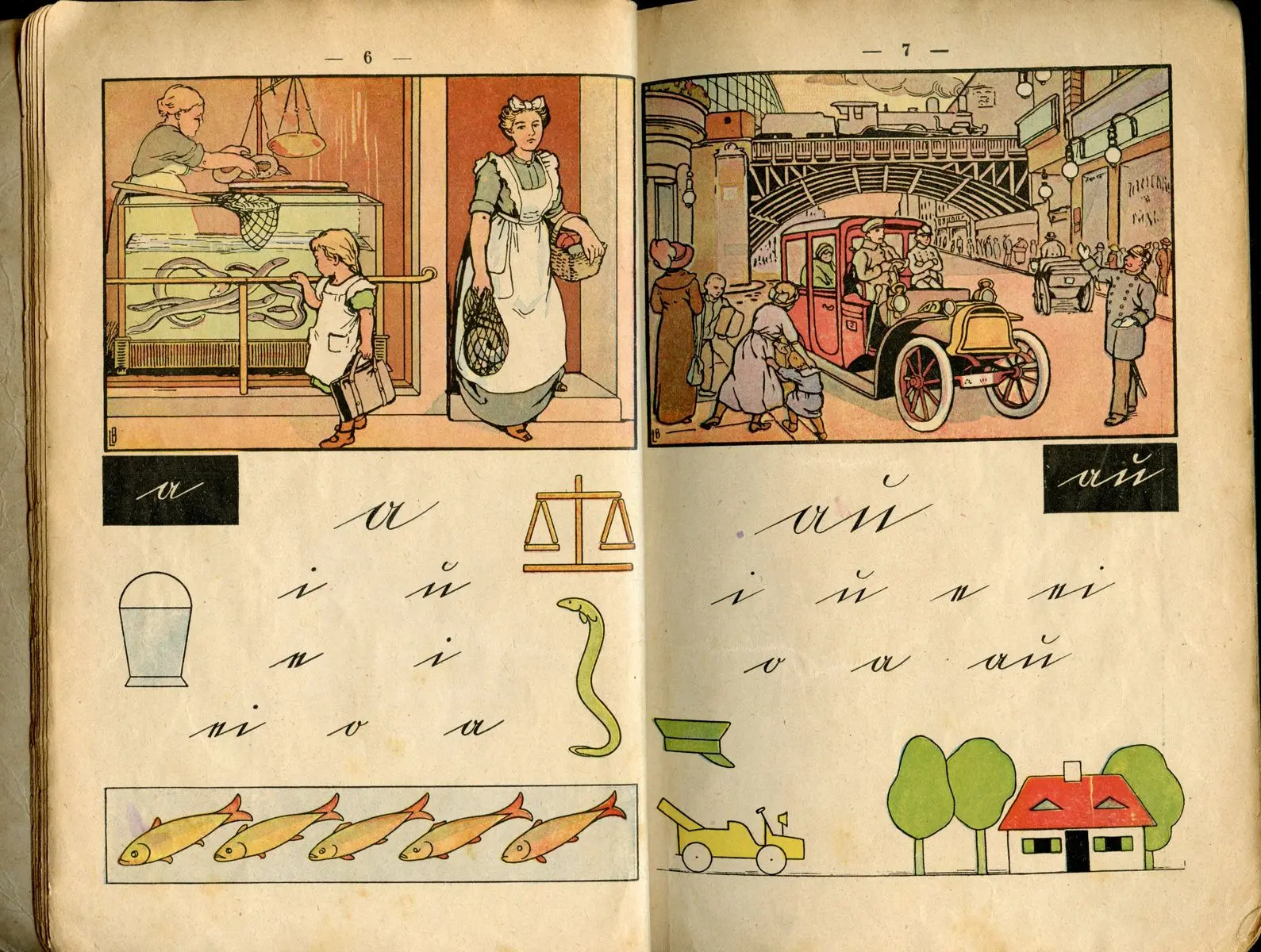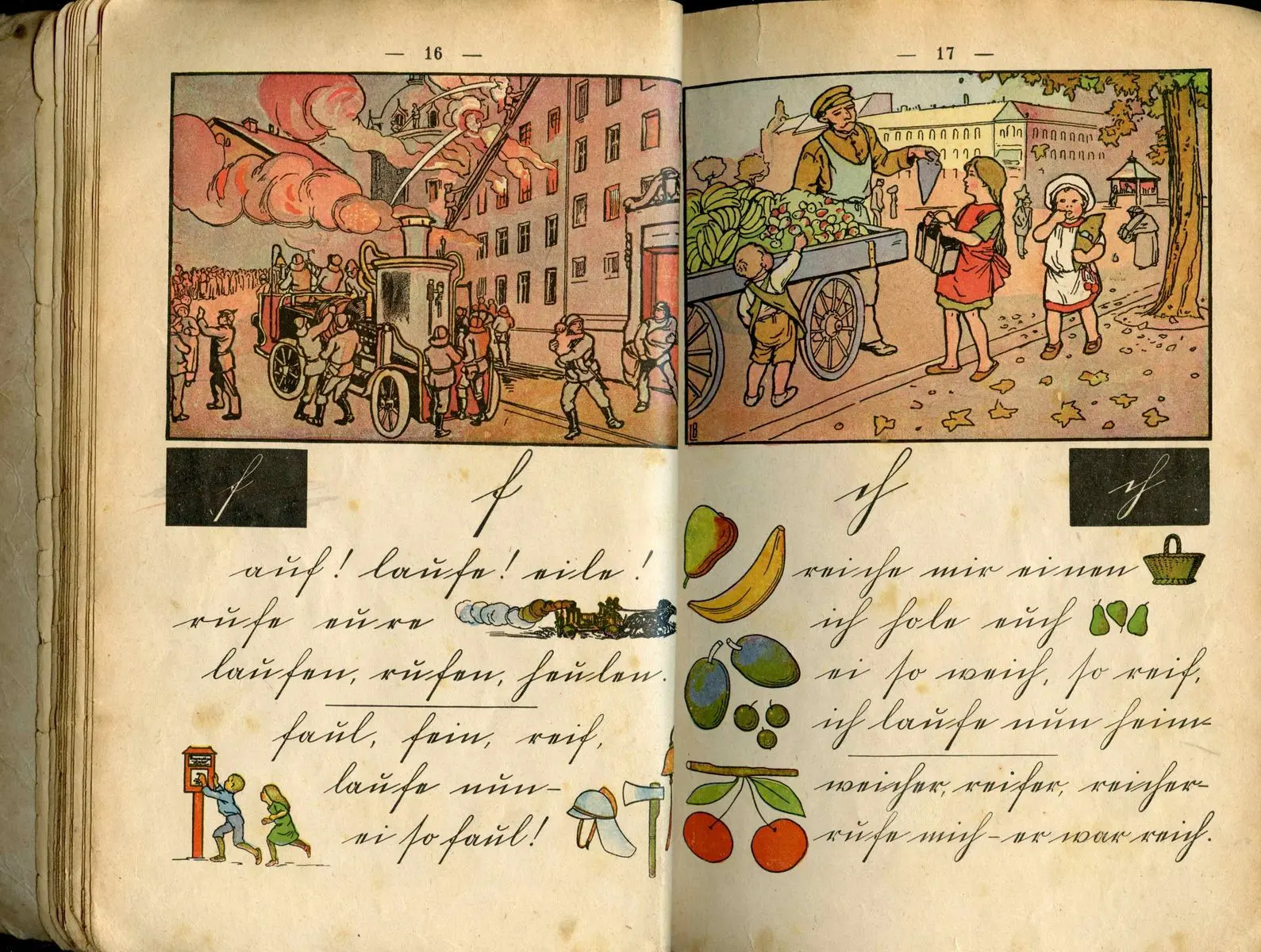
habe mal 3 Seiten einer Fibel von 1920 hochgeladen, weil sie mir immer wieder ansehenswert erscheinen. Vielen Dank auch gleichzeitig an ERNABURGA für die Anmerkungen zu meinem Beitrag. Gleichzeitig Gruß nach Dresden. Im vergangenen Jahrhundert wurde ich dort in Johannstadt geboren.
• Wäre es möglich, die genauen Referenzen zu dieser Fibel zu liefern? Ich frage das auch vor dem Hintergrund, dass ich seit längerem alte Fibeln erkunde zu ihrem Schriftduktus vor Sütterlin. Gibt es auf Buchdeckel bzw. der Titelseite oder in einem Vorwort irgendwelche Hinweise zu Schreibschrift, also welche das ist (z.B. Preuß. Normal-Alphabet, Bayerische Normalschrift, Badische Normalschrift, Württembergisches Musteralphabet, …) und vielleicht sogar von wem die Schreibschrift stammt? Am interessantesten sind dabei vor allem die Großbuchstaben. An denen erkennt man oft den Duktus. … Gibt’s in der Fibel eine oder 2 Seiten mit dem gesamten Kurrent-Alphabet?